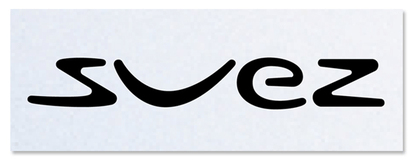
Voici quelques semaines le portail de noos laisse apparaître la nouvelle mouture de l’identité visuelle de noos transformé en noos upc puisque racheté récemment (2004) par l’américain Liberty Media.
Voici l’ancien et le nouveau logo:
le logo du groupe suez que voici :
et le bandeau du portail des abonnés du cable (au jour d’aujourd’hui 25 octobre 2006) :
Le précédent logotype de noos correspondait à un véritable effort visuel pour identifier le cablo-opérateur par rapport à ses concurents ADSL. La prise télé transformé en prise sur le net était une trouvaille tout à fait correcte, tout en restant dans une sobriété minimaliste.
A l’époque noos était détenue par le groupe suez qui venait aussi de relooker son identité avec l’agence W & Cie qui pour l’occasion remporta un grand prix Stratégies de l’identité.
Suez «lâcha l’affaire» en 2004, au profit de Liberty Media et d’UPC et nous voici aujourd’hui avec un logotype noos relooké pour courronner cette transaction.
Ce que j’en pense :
1) tout d’abord je ne comprends pas la présence du N au-dessus du logo noos. Non que je sois «imperméable» mais il me semble que dans l’espace du bloc-marque les deux ensembles de signes se font une concurrence graphique dont aucun ne profite réellement.
2) le N au-dessus de noos n’est pas sans rappeler le dessin du logo de suez, alors que l’ancien actionnaire s’est déjà séparé de sa filiale. Incompréhensible stratégie graphique si l’on n’est pas dans le saint des saints de la présidence du groupe noos-upc. L’inconscient graphique de la «ménagère» qui regarde ses factures, et ses brochures newsletter s’y perd, et mon inconscient de graphiste se réveille avec une acuité étrange sur ce cafouillage. Ça doit avoir un sens, mais je ne le comprends pas. S’il vous plaît messieurs de la com de noos, manifestez-vous, les lecteurs de ce blog aimeraient savoir.
3) le nouveau dessin du logotype noos, bien que très tendance bauhaus-hype, laisse filer une mine d’or avec l’ancien dessin. En effet le positionnement du cable sur l’offre des FAI multiservices (télé+net+téléphone) est assez exceptionnelle, à l’heure où l’on aborde sur l’ADSL les problèmes de bande passante nécessaires pour l’offre d’une qualité d’image télé associée à l’internet haut débit. Noos bien que chère, et ne bénéficiant pas d’une hotline des plus performants, se situe plutôt dans la tranche qualité de ces solutions hybrides. Alors je ne comprends pas que l’on ne capitalise plus sur cette identité forte pour revenir vers un dessin tendance sans âme et aucun démarquage.
4) la présence sur le bandeau du portail de l’ancien et nouveau logo me laisse aussi complètement perplexe quant à la pertinence d’une stratégie claire. Ça me fait penser bien sûr au cafouillage de l’identité du Le Crédit Lyonnais où l’on a vu pendant de longs mois la co-existence de l’ancien et nouveau logo sur les agences du groupe. Mais là où il s’agissait sans doute d’un problème d’investissement majeure de mobilier en dur, un bandeau de portail lui, ne coûte pas grand chose à mettre à jour. Du coup mon interrogation porte exclusivement sur la responsabilité d’un service de com et non des budgets lourds à débloquer.
5) je ne comprends pas non plus la nécessité de changer tous les 4-5 ans un logotype, lorsqu’on sait le temps qu’il faut pour l’installer durablement dans l’inconscient des consommateurs. Investissement jetable, les logotypes une fois de plus font les frais d’une stratégie mystérieuse où ce ne sont plus les entreprises qui repensent leur marque mais les dircoms qui veulent marquer leur territoire. Sujet de débat, sujet polémique, mais je suis ouvert bien entendu à toute opinion de la part des responsables de la com de noos à condition que ce ne soit pas moi qui soit obligé de les appeler à 0,34 centimes d’euros à la minute d’attente ;-)
Note subsidiaire : pour faire suite à certains commentaires j’ai donc déniché aussi l’origine du nouveau logo de noos ainsi que l’explication du N avec le point en dessous: le point du i de numericable.
Pour le coup on se rend compte que le logo de noos a été conçu par des martiens qui ont atterri sur la planète terre en continuant de parler venuséen. Ceci étant, le contraste ici se tient mieux entre les deux items (N + numericable). Quant à la déclinaison sur noos, elle est totalement «décablée» de la réflexion originale ;-)